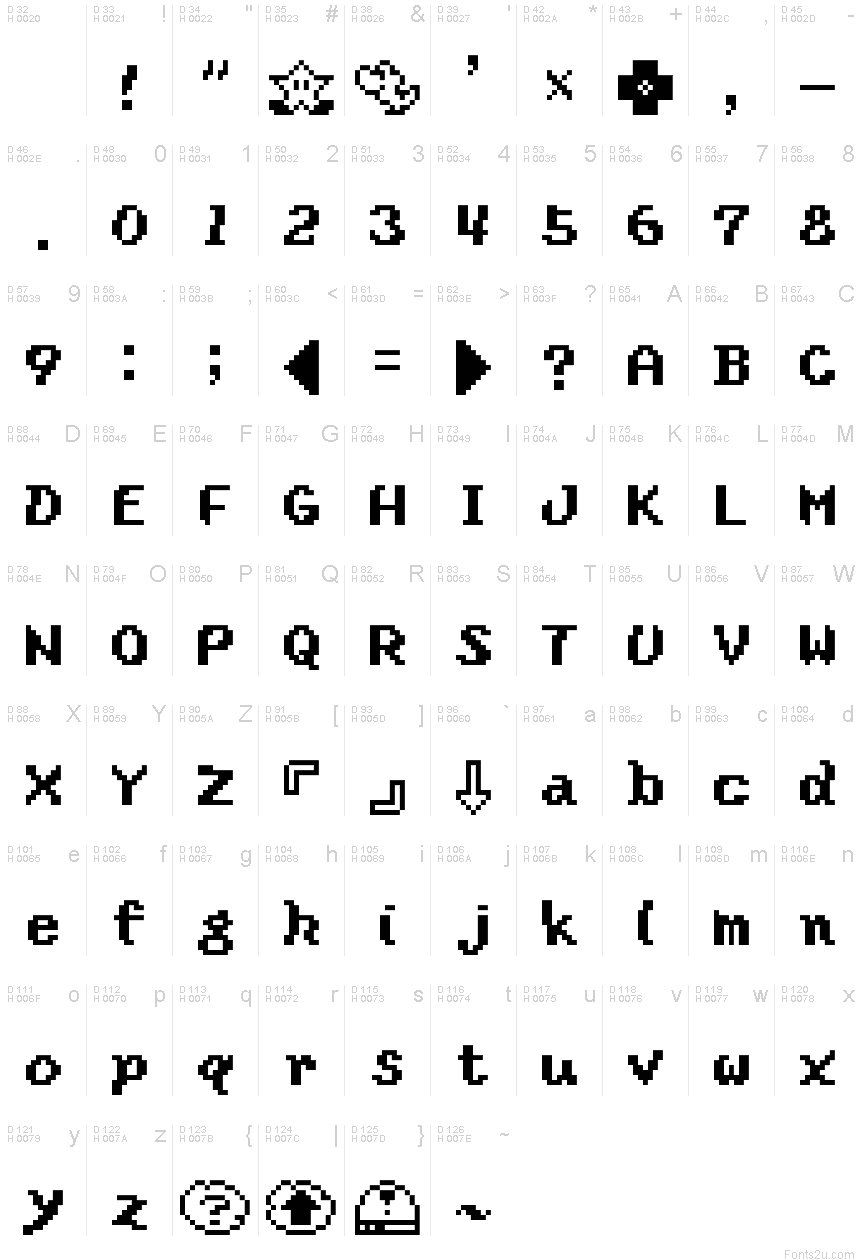
Yoster Island, bezplatné bitmapové písmo od codeman38, sází na robustní litery éry raných monitorů s hravým šmrncem domácích počítačů. Písmena jsou tvořena velkými čtvercovými schody a ostrými rohy, ale rytmus zůstává uvolněný a přátelský, takže působí méně strnule než mnohé jiné bitmapové návrhy.
Přirozeně zapadne do menu retro her, plakátů s nádechem arkád, nadpisů zinů, úvodních obrazovek nebo kompaktních log, kde tento "hranatý" odraz může vyniknout. Jakožto font zdarma se Yoster Island skvěle hodí i na titulky, streamovací grafiku a krátké štítky v rozhraní, zejména pokud chcete pixely, které působí hřejivě a ne jen technicky.
Yoster Island